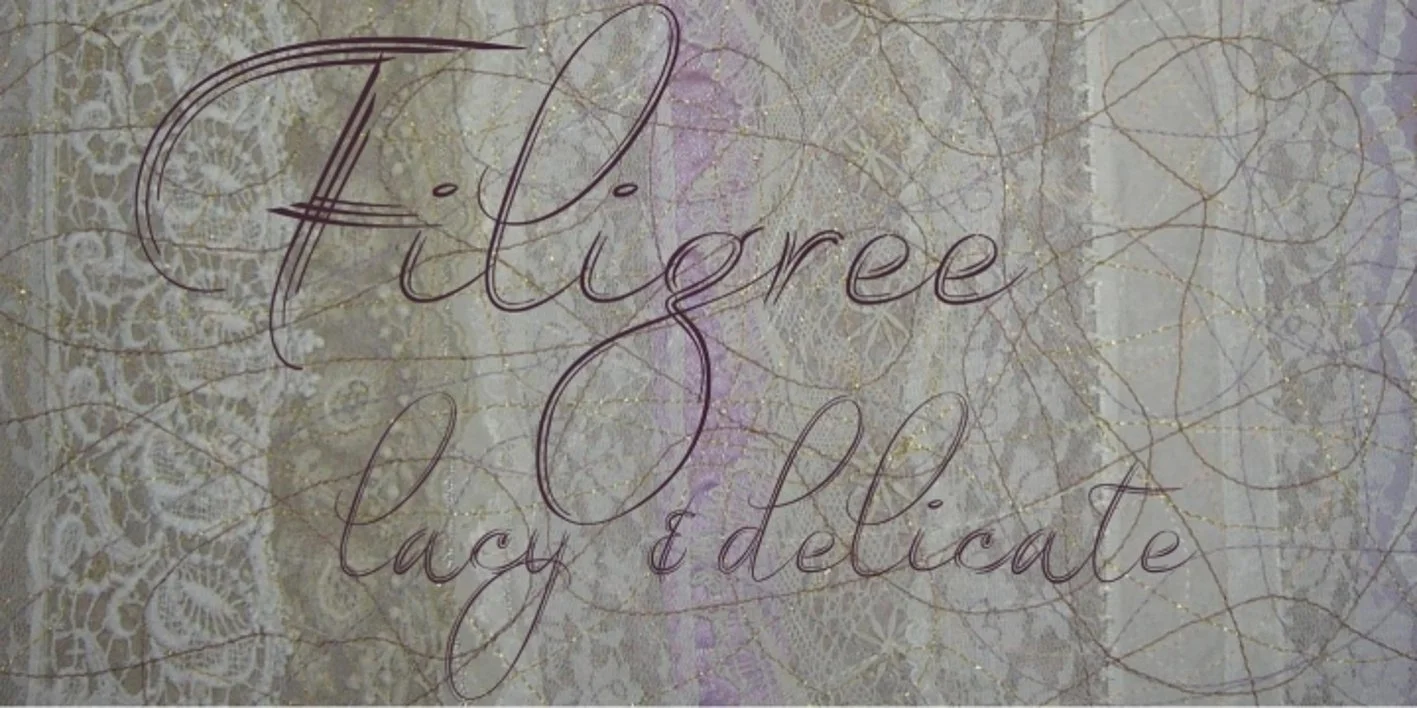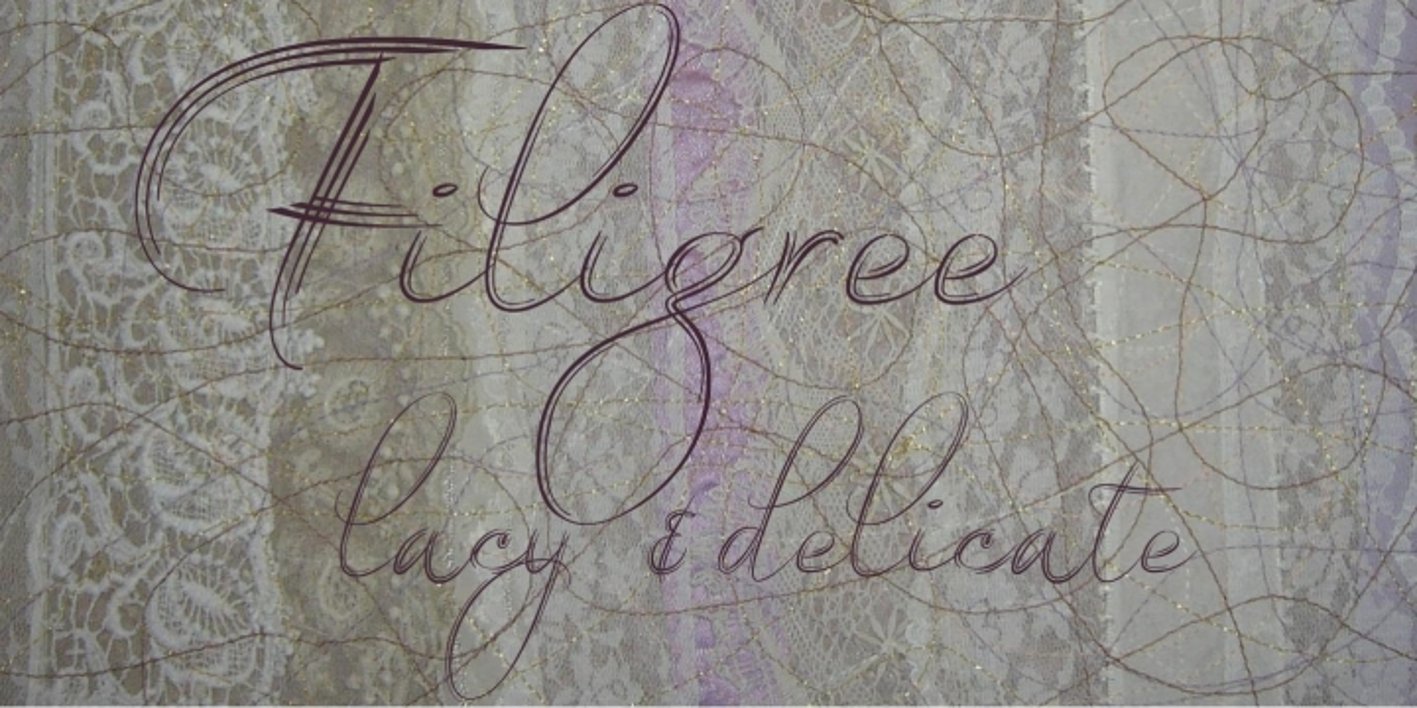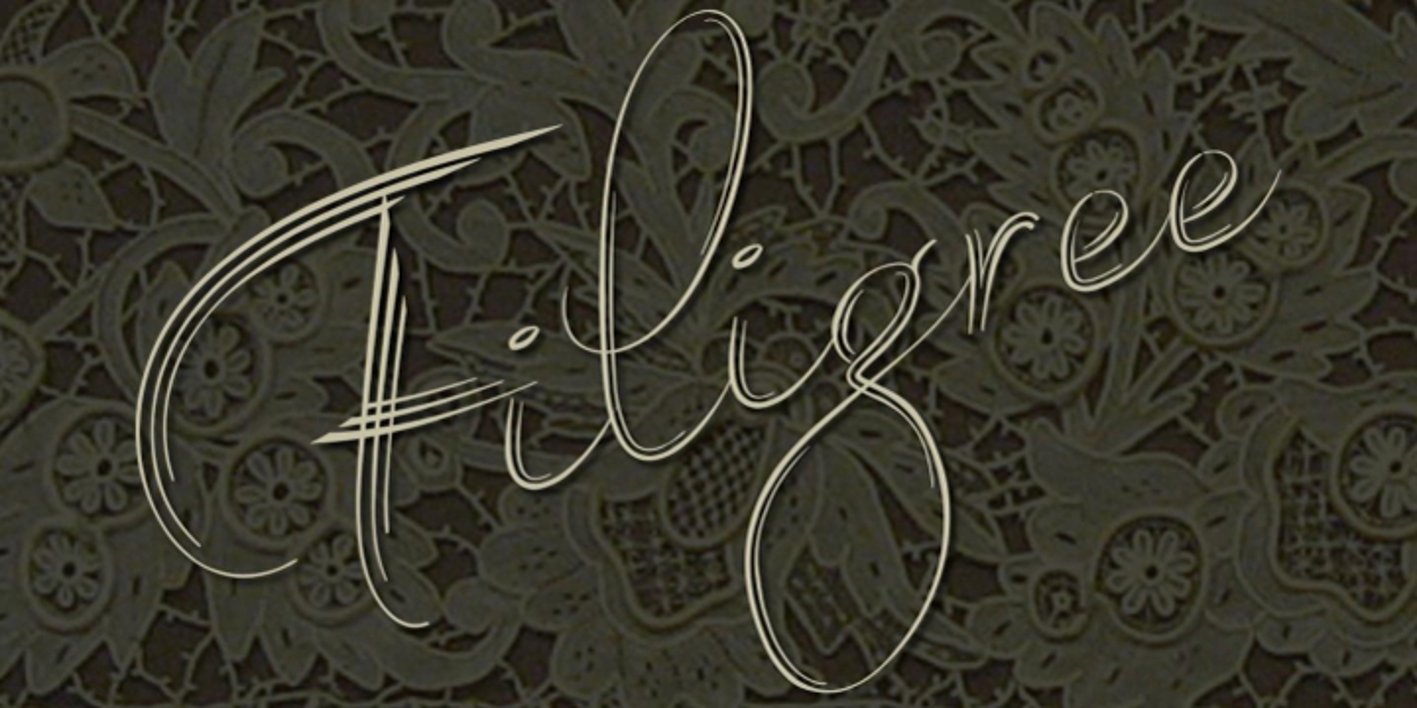
Filigree Font
Das filigrane Design, das an die filigranen Spitzen und Schmuckstücke erinnert, die im Europa des 16. bis 18. Jahrhunderts hergestellt wurden, wurde von Font Always und der Art und Weise inspiriert, in der die Fäden (oder filia) der Figuren in Always ineinander verschlungen sind. Er hat einen weichen, duftigen Charakter. Er eignet sich am besten als Ausstellungsstück Font in einem relativ großen Format. Bei einer zu kleinen Größe geht die Zartheit der einzelnen Fäden verloren. Die besten Ergebnisse erzielt man auch mit einer Kombination aus Groß- und Kleinbuchstaben. Die Verwendung von Großbuchstaben allein sieht nicht so gut aus. Alternativzeichen und Ligaturen sind ebenfalls enthalten. Wenn Ihr Anwendungsprogramm "Kerning" unterstützt, empfehle ich Ihnen, es einzuschalten. Dies ist zwar nicht unbedingt erforderlich, verbessert aber die Abstände zwischen den Buchstaben. Die Font enthält über 272 Zeichen (Groß- und Kleinbuchstaben, Interpunktionszeichen, Ziffern, Symbole und Akzentzeichen sind vorhanden). Sie enthält auch eine Reihe von "Open-Type"-Zeichen - diese erhöhen die Flexibilität der Font , indem sie Alternativen bieten, die entweder nach dem Ermessen des Designers verwendet werden oder durch die Umstände, unter denen die Font verwendet wird, bestimmt werden. Sie enthält alle Akzentzeichen, die in den wichtigsten europäischen Sprachen verwendet werden.